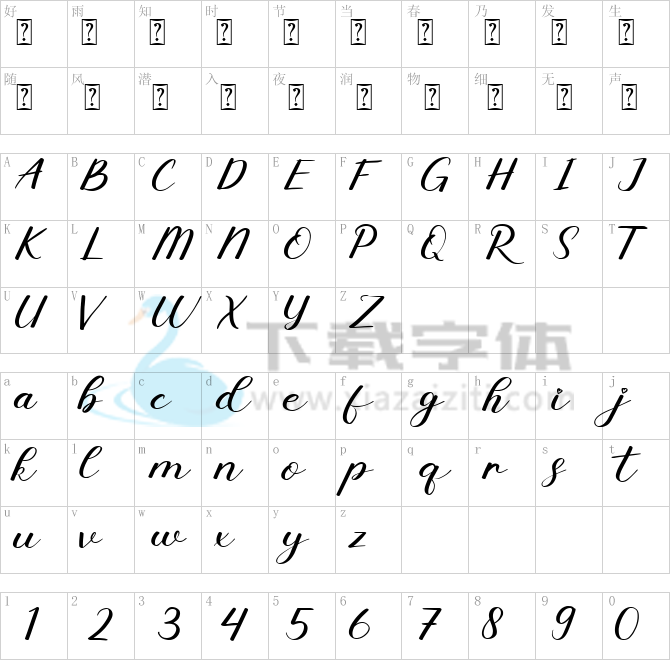
Aurona.ttf字体下载,这款字体结构工整、笔画清晰,兼顾美观与易读性,适用于标题、正文、海报、包装、LOGO 等多种场景。字形优雅稳定,风格百搭耐看,适配日常排版与创意设计,让文字呈现更舒适、更具质感。Aurona.ttf字体下载一笔一画,皆是细节,以均衡的比例、流畅的线条打造舒适视觉体验,字形端正大气,风格简约现代。无论是商业设计、品牌宣传还是日常排版,都能轻松驾驭,让文字更有格调与力量。Aurona.ttf字体下载字体下载。